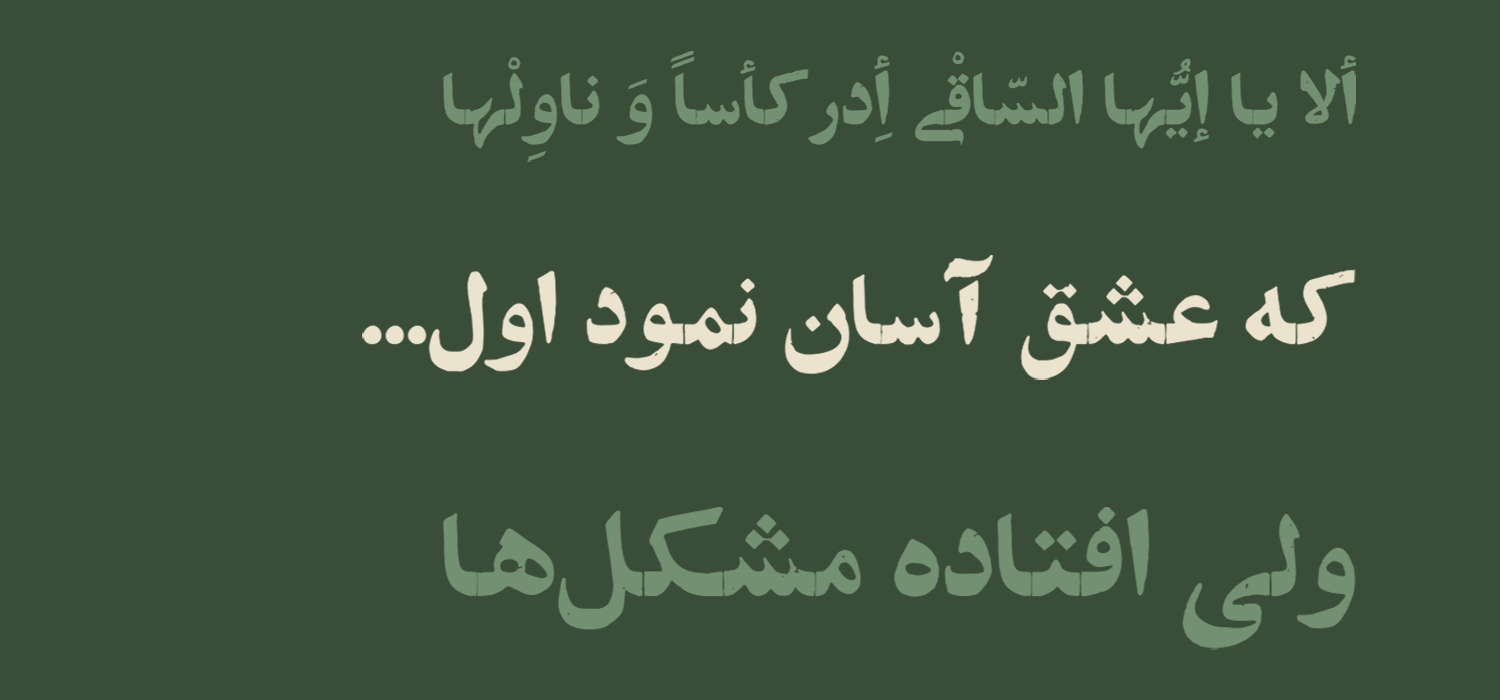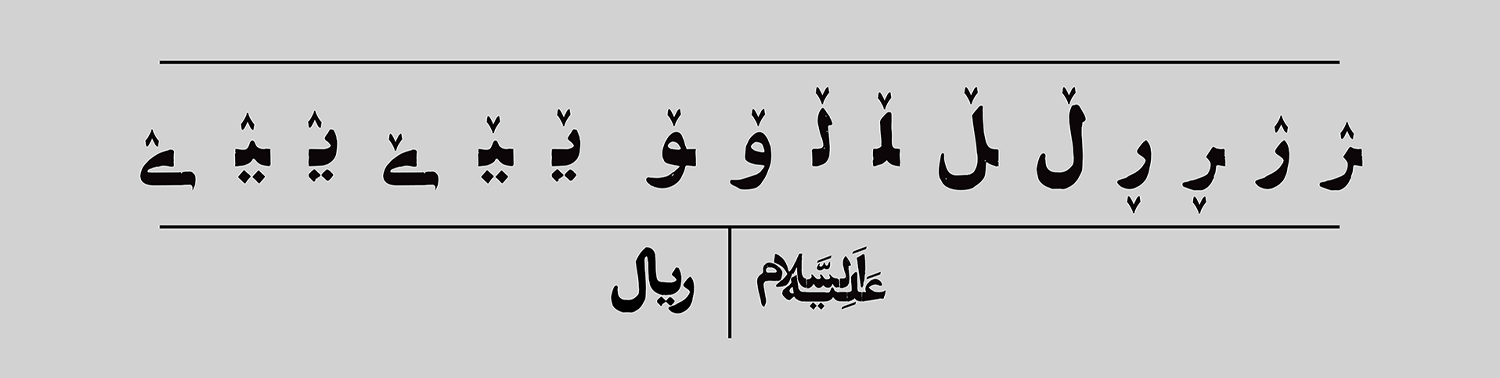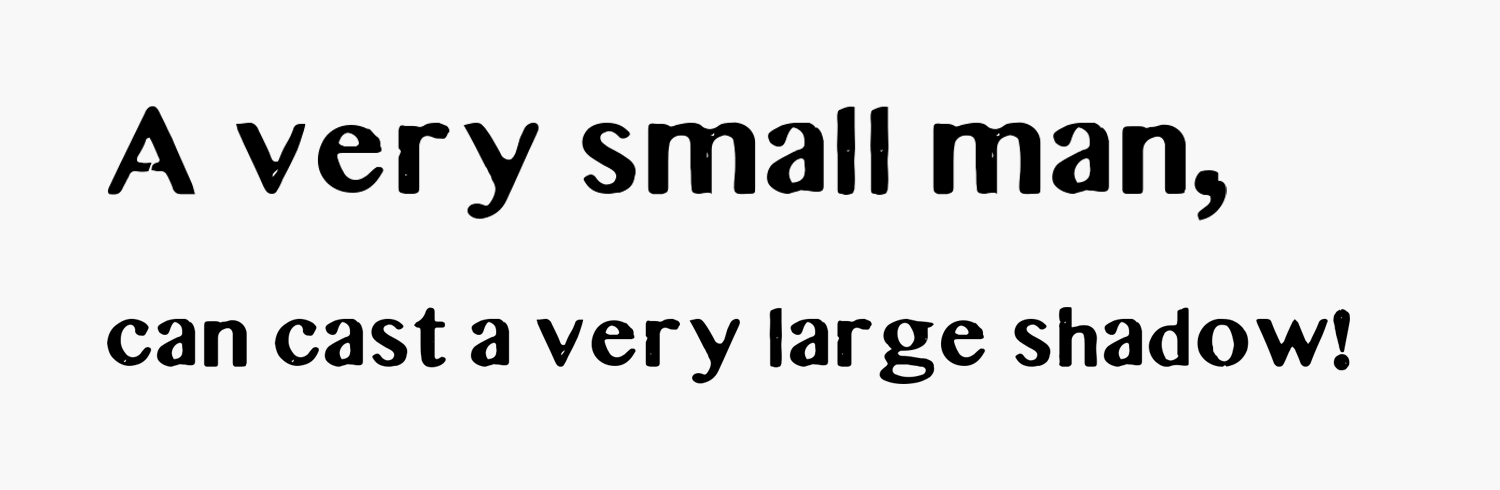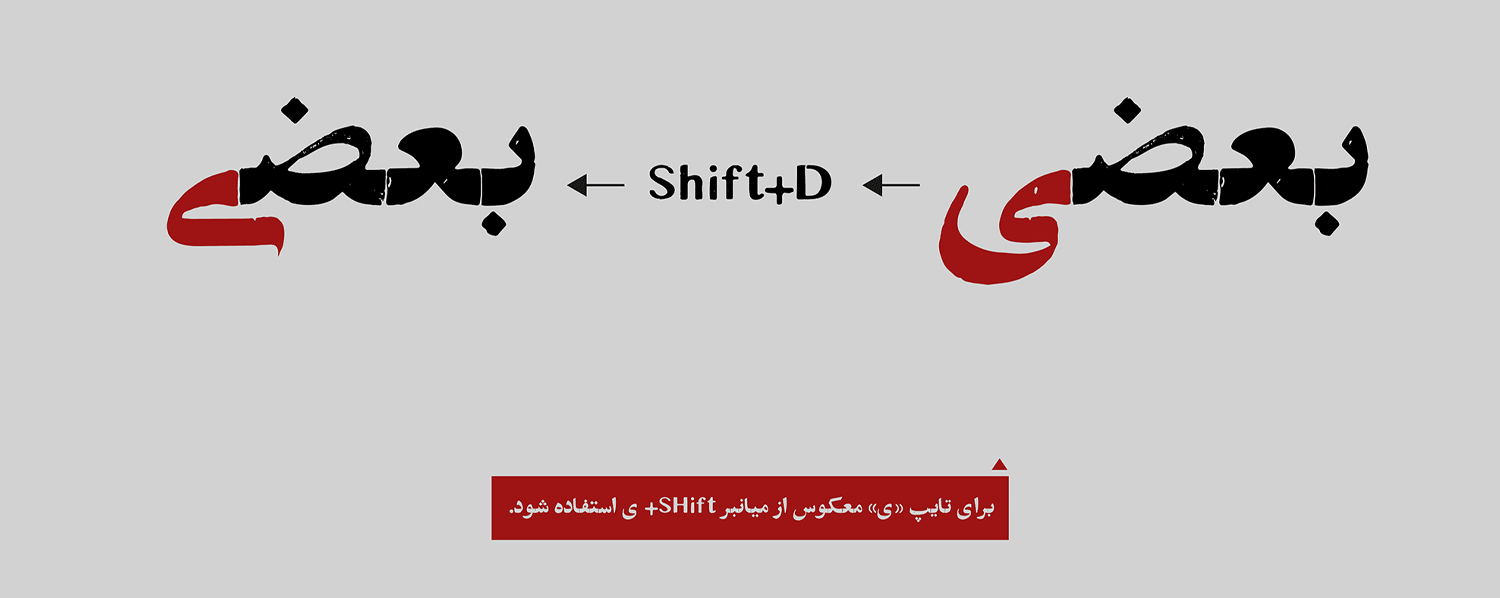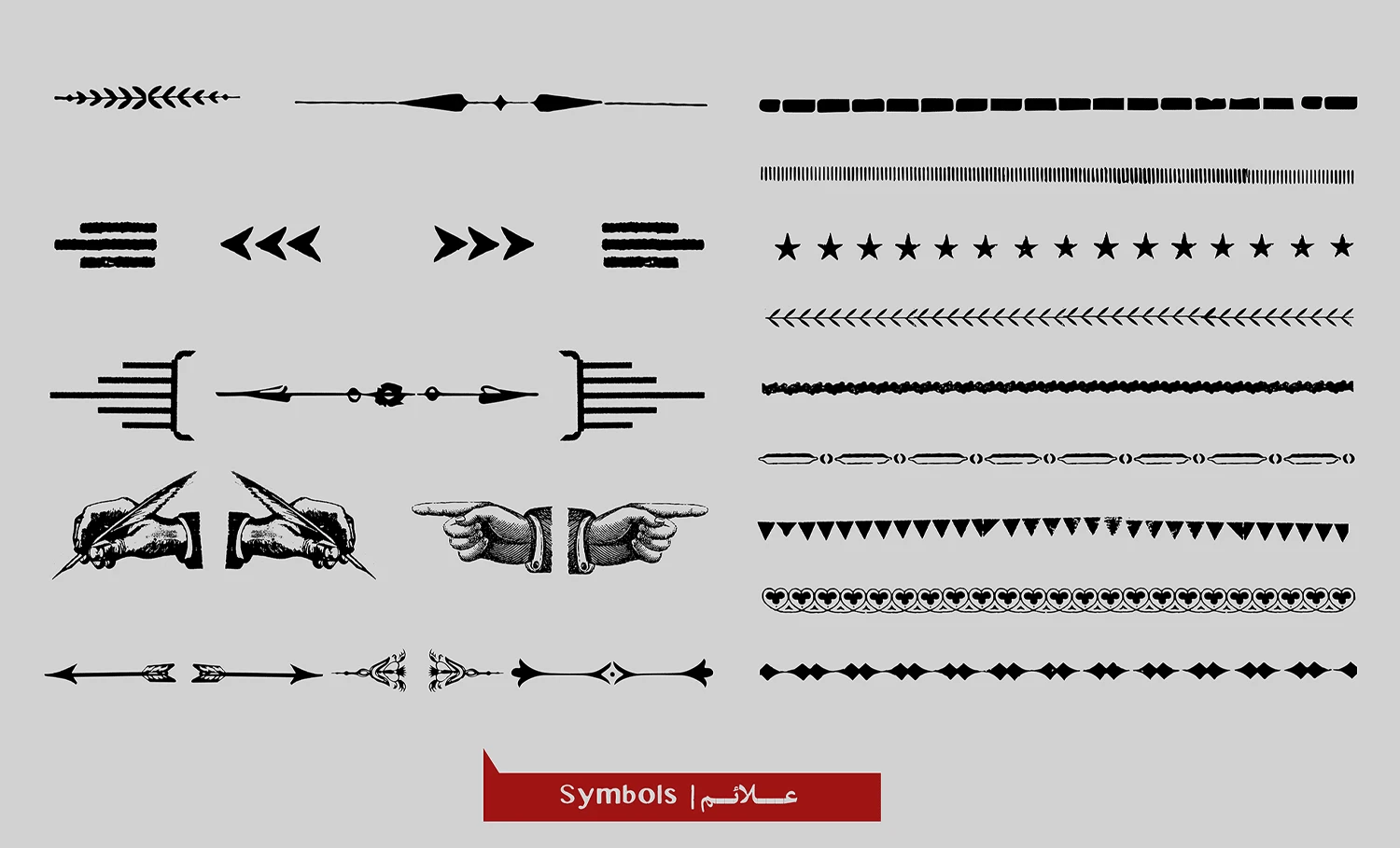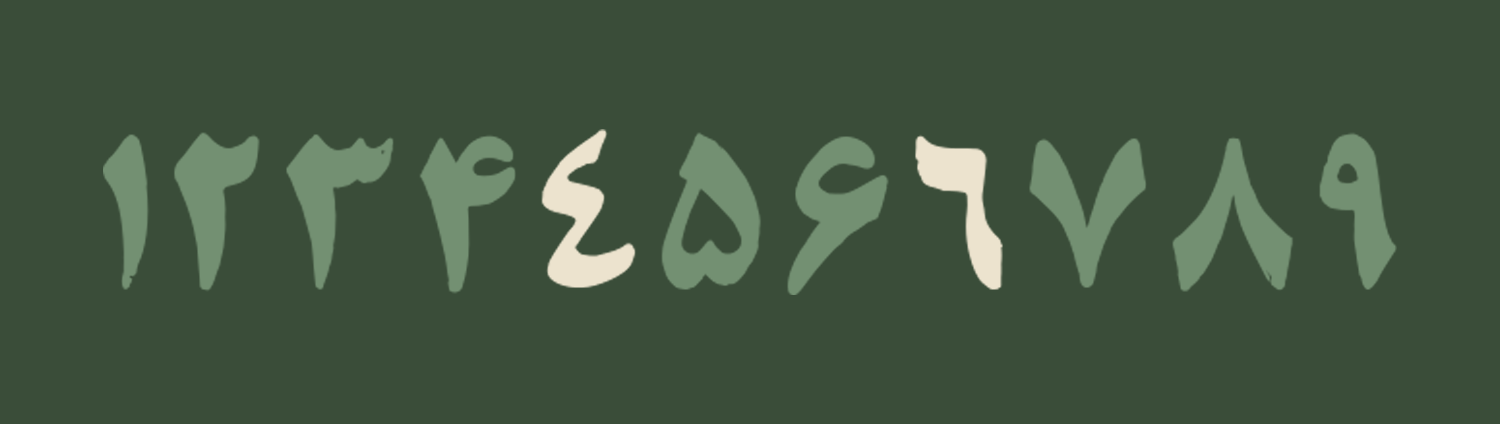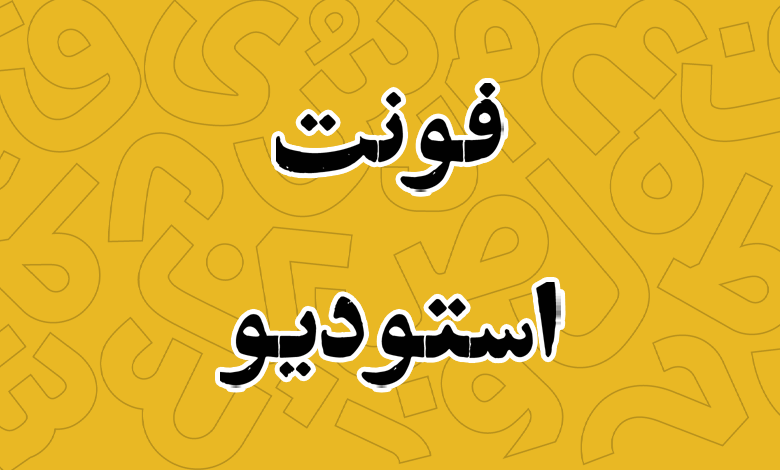
فونت استودیو (Studio)
فونت استودیو (به انگلیسی: Studio) قلمی به سبک دستگاههای چاپ در دوره پهلوی اول و دوم است که جزو گروه فونتهای قدیمی و نوستالژی بر پایه خط نسخ طبقهبندی میشود. این فونت با سبک آثاری از روزنامهها و کتب به جای مانده از همان دوران طراحی شده است.
طراحی فونت استودیو توسط استودیویی با همین نام و با همکاری رضا سالاریفر انجام گرفته است که نسخهای بازسازی شده از یک فونت قدیمی فراموش شده است که تا مدتها مورد استفاده قرار نمیگرفت؛ چرا که با ظهور نشر رومیزی به فونت قابل استفاده در نرم افزاریهای کامپیوتری تبدیل نشدند.
در ادامه این نوشته از سایت فونتچی به نقد و بررسی فونت استودیو خواهیم پرداخت. قلمی که با الهام از صفحات روزنامهها، مجلات و آثار بهجای مانده از نیم قرن گذشته الهام گرفته و باز سازی شده است تا برای استفاده در قالب نرمافزاری در دسترس عموم قرار گیرد.
بررسی و دانلود فونت استودیو (Studio)
برای ایجاد حس و حال کهنه و نوستالژیک، فونت استودیو دارای کمی خوردگی، بی نظمی در اتصال حروف و عدم تناسبات عمدی است. بنابراین اگرچه این حروف در زمان خود ویژه متن بوده است اما فونت استودیو یک فونت نمایشی محسوب میشود و مناسب ایجاد حس و حال قدیمی در آثار گرافیکی است.
این تغییرات عمدی نیز بنا به سلیقه طراح در قلم اعمال شده است تا صرفا مناسب برای مطبوعات و با آن سبک دوران صنعت چاپ نباشد؛ بلکه بتوانید از این قلم در کارهای نمایشی، تزئینی و گرافیکی نیز استفاده کنید.
سبک طراحی و وزن فونت استودیو
یکی از کاستیهایی که در حوزه فونت فارسی هنوز هم احساس میشود، کامل نبودن قلمی با حس و حال نوستالژی و قدیمی است. هرچند که پیش از این قلمهای دیگری نظیر فونت گرامافون، فونت صنعت یا فونت صداقت با همین ساختار معرفی شدهاند؛ اما با توجه به تنوع قلمها بر اساس سبک طراحی، کاربرد و خط مورد استفاده هنوز آن تنوع لازم وجود ندارد.
به همین جهت فونت استودیو با الهام از آثار چاپی آن دوران در دست طراحی قرار گرفت و نسخه نهایی آن چیزی شد که در این نوشته آن را مشاهده میکنید تا جزو این گروه فونتها باشد. این قلم همان حس و حال قدیمی آن دهه را انتقال میدهد.
در طی مراحل بازسازی، به تغییر شکلی (دفرماسیون) که پروسهی چاپ سـربی با گذر زمان در ریخت حروف به وجـود میآورد وفادار بودیم. شکل حروف و اتصالات تناسب دقیقی با هم ندارند، بعـضی بهصورت صحیح بر روی خط کرسی قرار ندارند و تناسب و اندازهی حروفِ همسان لزوماً شبیه به یکدیگر نیست. در محیط و سطح حروف بافتها و خوردگیهایی مشاهده میشود که تلاش کردیم همه را حفظ کنیم. همچنین در نسخه نهایی، کاراکترهای اول، وسط، آخر و تنهای حروف، هر کدام شکل و بافتِ مختص به خود را دارند و اینطور نیست که مثلاً خانواده حروف «س» و «ش» تنها با اضافه کردن چند نقطه ساخته شده باشند.
پشتیبانی از ۴ زبان متنوع
فونت فارسی استودیو محدود به زبان فارسی نبوده و از سایر زبانهای رایج که در ایران مورد استفاده قرار گرفته و بر پایه رسم خط فارسی و انگلیسی است پشتیبانی کاملی دارد.
در این بین زبان عربی و زبان کردی بیشترین سازگاری را در این قلم دارند که علاوه بر حروف مشترک هر دو زبان، اعراب به شکل کاملی رعایت شده است.
در زبان عربی کلیه اعرابی که در همنشینی با همزه، تشدید و سکون قرار دارند، با ساختاری در کنار هم قرار میگیرند که هم فاصله با حروف قبلی یا بعدی رعایت شده و هم اینکه از نظر ارتفاع و خط کرسی در استانداردی قرار دارند که ساختار فونت را فشرده یا مرتغع نکند.
یا در زبان کردی که استفاده از برخی گلیفهای تزئینی بر روی حروف بسیار رایج است پیاده سازی شده است تا برای این زبان بتوانید با یک استاندارد درستی تایپ خود را انجام دهید.
این قلم همچنین از برخی گلیفهای پر کاربرد مثل «ریال» و «علیهالسلام» پشتیبانی میکند که در تصویر نمونه آنها را مشاهده میکنید.
ساختار قلم استودیو در زبان انگلیسی نیز با همان سبک فارسی پیاده سازی شده است. در برخی حروف بهدلیل تغییر ساختاری سربی حروفچینی دستگاههای ماشینی همان جاهای خالی، زوائد و خوردگیها نیز پیاده سازی شده است.
شاید تنها ایرادی که بتوان از نظر زبانی به این قلم گرفت، پشتیبانی عدد «۵» عربی باشد که در آن پیاده سازی نشده و در ادامه نیز به اعداد کامل قلم اشاره خواهیم کرد.
دارای ترکیبات و حروف جایگزین
فونت استودیو دارای ترکیبات و حروف جایگزین است که امکان تایپ کلمات را در چند حالت مختلف در اختیارتان قرار میدهد. به عنوان نمونه در تصویر زیر میبینید که «ی» پایانی برای کلمه مورد نظر میتواند به «ی» معکوس تبدیل شده و ظاهر کلمه را به ترتیب دیگری تایپ کنید.
وجود چنین ترکیباتی علاوه بر زیبایی، موجب جلب توجه کاربر به برخی کلمات و عباراتی خواهد شد که در طراحی شما از اهمیت بالایی برخوردار هستند. خصوصا اگر قرار باشد با هدف تبلیغات از این قلم استفاده کنید.
دارای گلیف های تزئینی و کاربردی متنوع
ویژگی دیگر این قلم پشتیبانی از گلیفهای تزئینی و کاربردی است که در آثار بهجای مانده از همان دوران الهام گرفته شده است. این گلیفها را میتوان در تیترها، ابتدای پاراگراف و بخشهای مختلف دیگر با توجه به سلیقه خود استفاده کنید که پیش از این نمونه آن را در فونت دفتر که توسط همین طراح ساخته شده دیدهایم.
پشتیبانی از اعداد فارسی و عربی
این فونت از اعداد فارسی و عربی به صورت مشترک پشتیبانی میکند که بر اساس زبان انتخابی سیستم عامل اعداد تایپ خواهند شد. اگر فارسی باشد اعداد فارسی، اگر انگلیسی و عربی هم باشد اعداد همان زبان تایپ میشود.